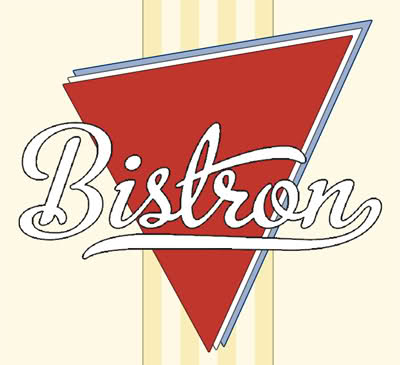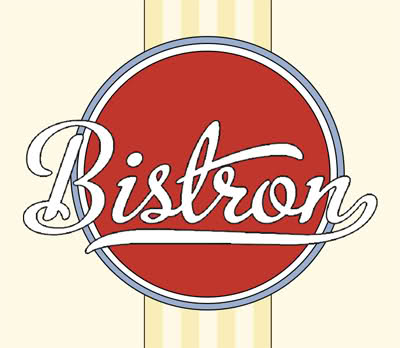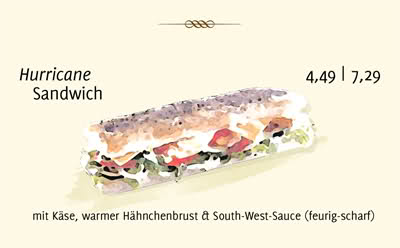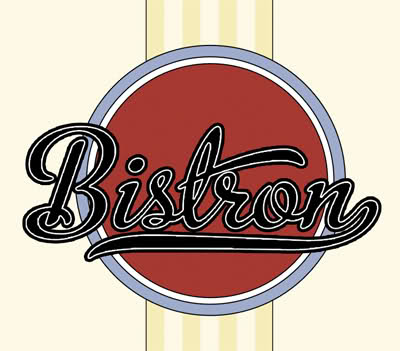
Weiche Serifenlose gesucht
Ich gestalte gerade das CD für einen Gastronomiebetrieb. In groben Zügen sieht im Entwurf schon alles so aus wie ich mir das vorstelle, nur mit Der Schrift für die Texte in Drucksachen wie zB. der Menükarte breche ich mir im Moment noch einen ab...
Was ich suche ist eine Serifenlose (von einer Serifenschrift bin ich abgekommen, wirkt zwar edel und warm aber in Verbindung mit der Schrift im Logo dann zu altmodisch) die nicht konstruiert wirkt, edel, weiche Formen...
Die Delicious http://www.josbuivenga.demon.nl/delicious.html (insbesondere ihre Kursive) geht schon ziemlich in die Richtung, mit ihren sanften Schwüngen, trifft es aber noch nicht völlig...
Ohne das Logo gesehen zu haben und zu wissen, ob das eine Gastro-Verwaltungsgesellschaft oder eine Eckkneipe ist, kann man nur raten.
Ich rate mal:
Eine elegante, weiche Kursive hat z.B. die Graublau Sans (siehe rechte Spalte).
Typografski & hey: Nice :D Trifft es aber leider noch nicht so ganz :(
Weil ich mich offensichtlich noch nicht ganz unmissverständlich ausgedrückt habe und Herr Pachulke Recht hat, hier mal zwei Bilder und eine etwas bessere Erklärung:
Das ist das Logo wie ich es mir bisher vorstelle:
Und solche Sandwiches machen die unter anderem:
(beide Bilder noch im Entwurfsstadium in Photoshop)
Das Unternehmen ist vor 8 oder 9 Jahren mal nach der Idee von SubWay entstanden... Dementsprechend sieht das aktuelle CD auch recht Fast-Food-mäßig aus. Jetzt sollen einige neue Filialen entstehen, und ich konnte den Besitzer davon überzeugen, dass er nicht als direkte Konkurrenz zum Vorbild auftreten sollte... Damals hätte das vielleicht noch funktioniert, aber heutzutage, wo die an jeder Ecke einen Laden haben... Ausserdem hat er sein Angebot auch noch erweitert und wird das auch noch weiter tun, bevor die neuen Filialen Realität werden. Die Einrichtung des Ladens und die Qualität des Angebots sind auch eine kleine Stufe über dem angesiedelt was SubWay bietet. Dementsprechend ist mein Entwurf bewusst eine Ecke edler als die Vorlage.
Allerdings soll das neue CD sich auch nicht zu weit vom alten entfernen, also bin ich zB. auf die Streifen (waren vorher im Menü etc. seitenfüllend...) und das Blau-Rot (war vorher viel knalliger und mit Reflief und Reflexionen, plastikmäßig...) festgelegt.
Die Illustration des Sandwiches ist aus einem Foto entstanden das vorher im Menü war.
Ursprünglich wollte ich die Texte in einer Serifenschrift setzen, aber mittlerweile bin ich davon abgekommen... Das ganze sieht dann zu 1920 aus... Das ist dann zu weit vom ansatzweisen Fast-Food-Charakter des Ladens entfernt.
Was mir vorschwebt ist also eine Serifenlose, jedoch nicht Futura oder Univers, sondern etwas weiches, gerne auch mit einigen verspielten Anklängen oder alternativen Glyphen, quasi eine Serifenschrift ohne Serifen... -seufz- Nicht einfach, ich weiß ;)
… quasi eine Serifenschrift ohne Serifen …
Also als Kompromiß eine Semi-Serif … also Rotis! :party:
Nee, sollte ein Scherz sein. Aber im ernst: Hast Du Fontin schon mal probiert? Die scheint mir sehr gut zum Schriftzug zu passen.
Vielleicht die Parisine? Hat auch eine sehr schöne Kursive (weicher als die von der Delicious). Wenns noch weicher/humanistischer/verspielter sein darf, auch mal die Parisine Plus anschauen.
Etwas weniger «fließend», aber auch sehr schön, wäre evtl. die Costa.
Und da mir keine Fonts von anderen Foundries einfallen, höre ich jetzt auf, sonst kommt das hier wie Porchez-Schleichwerbung :)
Pachulke, Du bist genial!! Fast so wie Typografski! Mit der Rotis gehts, das ist der Bringer! Warum bin ich darauf nicht selbst schon gekommen, wo ich doch sonst auch immer alles in Rotis setze! :biglove:
Ähm... das war ein Scherz...? Oh... :oops:
Na gut, mit der Fontin siehts auch nicht schlecht aus... ;)
Könnte einen Ticken schmaler laufen, aber ist zum Glück auch noch bis 6pt ganz gut lesbar... :) Geht jedenfalls schon mal in die richtige Richtung, und ich finde auch dass sie zur Logotype richtig gut passt :D Wenn sie jetzt noch den einen oder anderen etwas verspielteren Glyphen hätte... so ein kleines k mit Schleife statt "<", ein kleines f das unter die Grundlinie geht, solche Sachen...
Noch eine Idee? Irgendjemand? :D
NinaS: Hmmmmmmmmm... Die Parisine Plus gefällt mir ganz gut mit ihrem f und g und ihrem ganzen Ligaturen... Ihr fehlen aber die Strichstärkenunterschiede der Costa oder der Fontin... :( Kann man denn nicht mal alles haben, nur ein einziges Mal!? :cry:
Stimmt schon, genau das hab ich mich auch gefragt :-\
Hmmm… Angie? Hat schöne Strichstärkenmodulation, ist aber noch weniger weich.
Mal was ganz anderes, apropos Semiserif: Avance?!
Könnte hinhauen. Wirkt aber natürlich sehr anders und weniger «modern» als das, was Du gepostet hast (beim Sandwich).
Probiere Lisboa (Sans) von Ricardo Santos. Weiters: Dobra oder Priva Pro von Dino Dos Santos wären einen Blick wert.
der kunde will wiedererkennung, das ist logisch (das wollen sie fast immer) aber zu viel kompromisse führen zu keinen guten ergebnissen.
für mich ist das halt kein logo, sondern eine illustration, einfach zu viel schnick schnack.
schaue dir diese beispiel mal an.